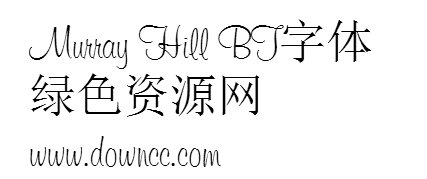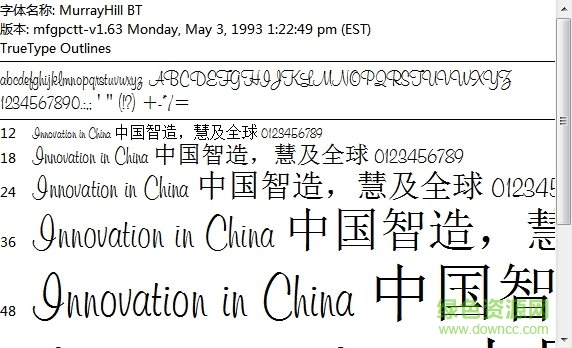
murray hill是一款書寫流暢簡潔的英文字體,中文字體延續(xù)了系統(tǒng)字體的清爽大方,英文造型較為突出,類似于手寫體的干練和緊湊,喜歡的小伙伴就來綠色資源網(wǎng)體驗(yàn)吧!
Murray Hill BT常用英文字體,風(fēng)格迥異而別致,給人十分活潑的視覺效果,給你的英文字體的引用更增添一股魅力。
murray hill是一款可以廣泛使用在平面設(shè)計(jì)、藝術(shù)設(shè)計(jì)、海報(bào)設(shè)計(jì)等領(lǐng)域的藝術(shù)字體,英文效果十分突出,讓文字擁有自己的個性,更便于帶大家留下深刻印象!